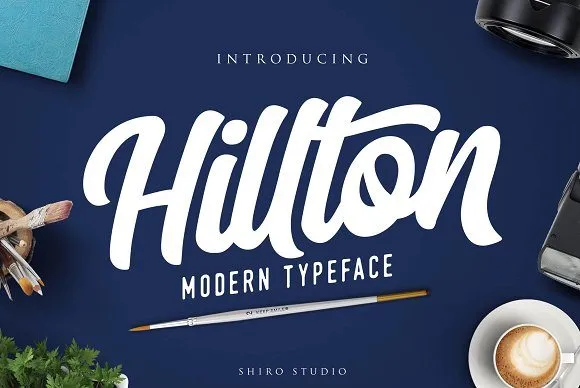
Hilton Script Font – Download Grátis
A Hilton Script Font é uma escolha perfeita para qualquer designer que deseja adicionar um toque autêntico à sua obra de arte digital. Esse moderno e elaborado tipo de letra garante um aspecto dinâmico, com seus recursos Opentype que permitem maior personalização. Combinando estilos elegantes e habilidades artesanais, essa fonte é perfeita para uma ampla gama de aplicabilidades, incluindo assinaturas, cartões de papelaria, logotipos, tipografia de citações, capas de revistas ou livros, cabeçalhos de websites, roupas e embalagens. A sua versão script é perfeitamente adequada para criar um visual único que se destaca em qualquer projeto. Seja qual for o seu objetivo gráfico, a Hilton Script pode oferecer uma solução versátil e profissional.
Designer: Gfont